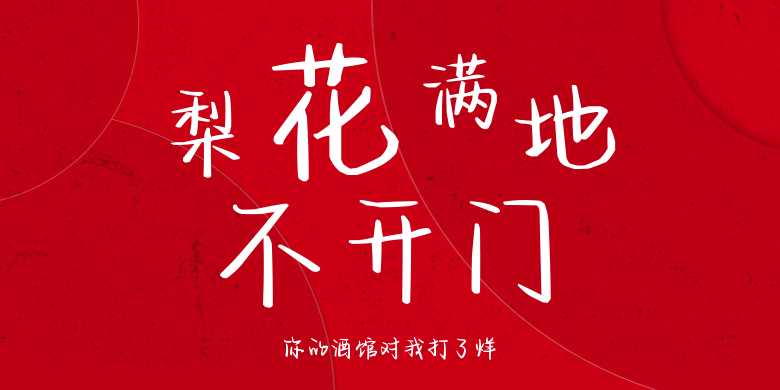
你的酒馆对我打了烊
你的酒馆对我打了烊,这款字体结构工整、笔画清晰,兼顾美观与易读性,适用于标题、正文、海报、包装、LOGO 等多种场景。字形优雅稳定,风格百搭耐看,适配日常排版与创意设计,让文字呈现更舒适、更具质感。你的酒馆对我打了烊一笔一画,皆是细节,以均衡的比例、流畅的线条打造舒适视觉体验,字形端正大气,风格简约现代。无论是商业设计、品牌宣传还是日常排版,都能轻松驾驭,让文字更有格调与力量。你的酒馆对我打了烊字体下载。